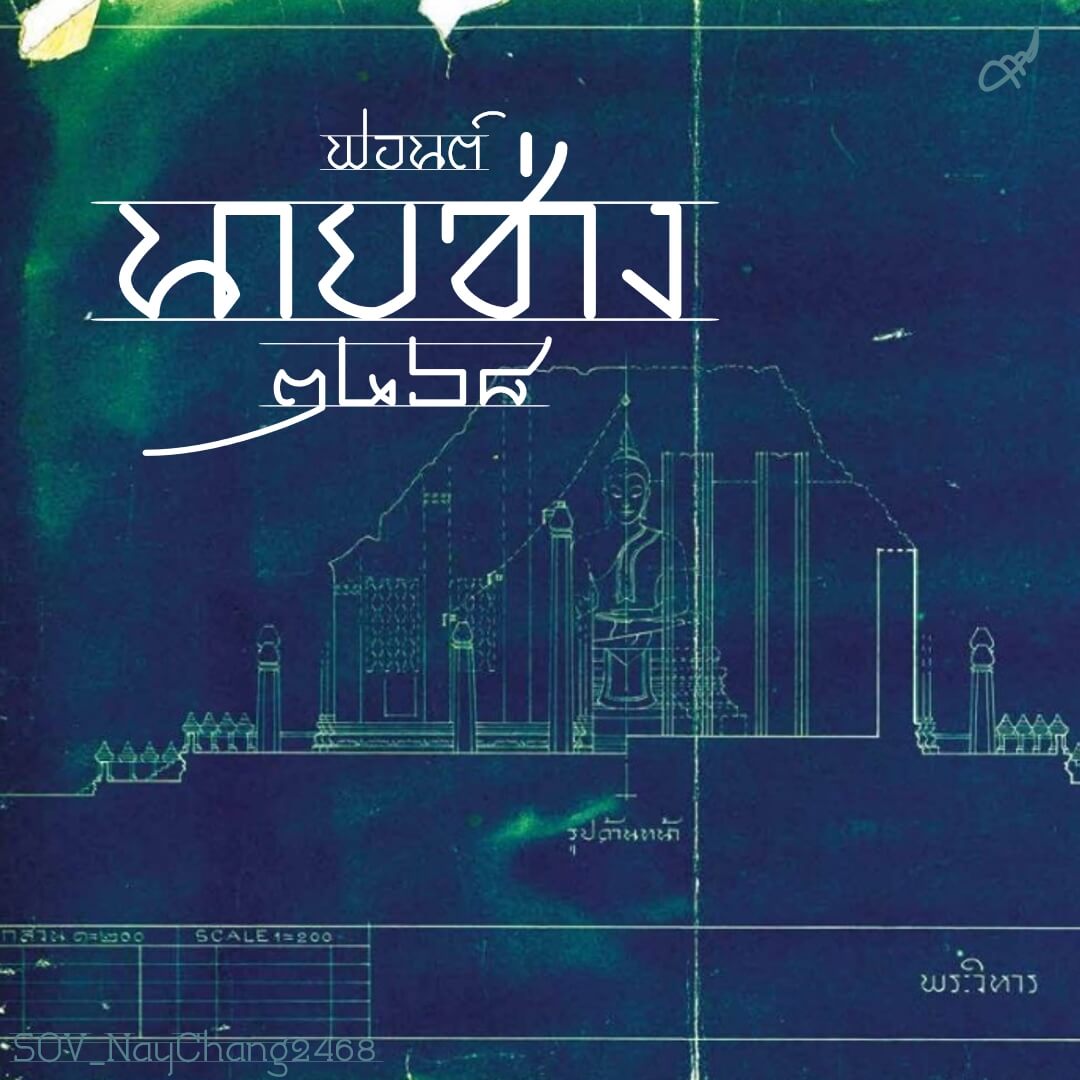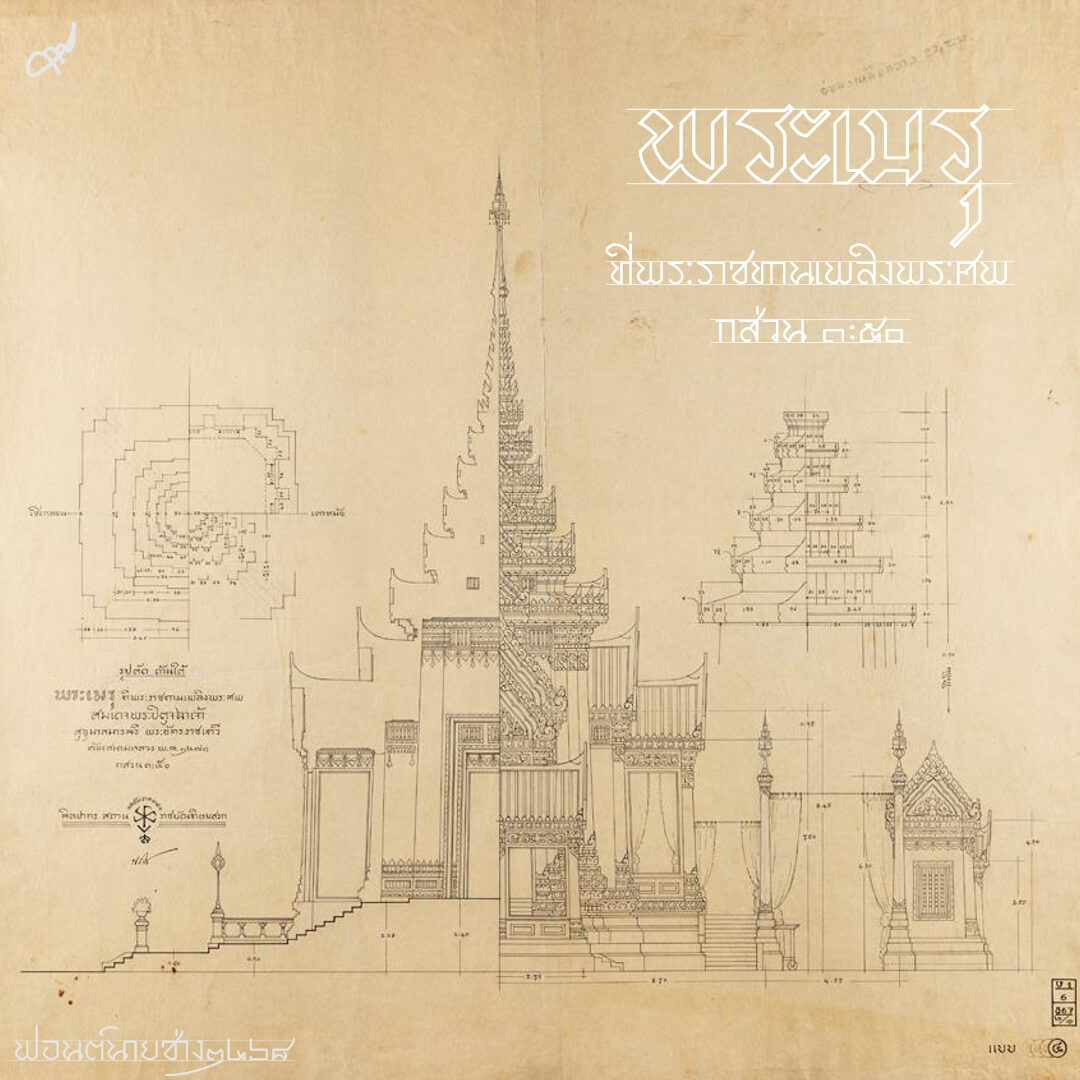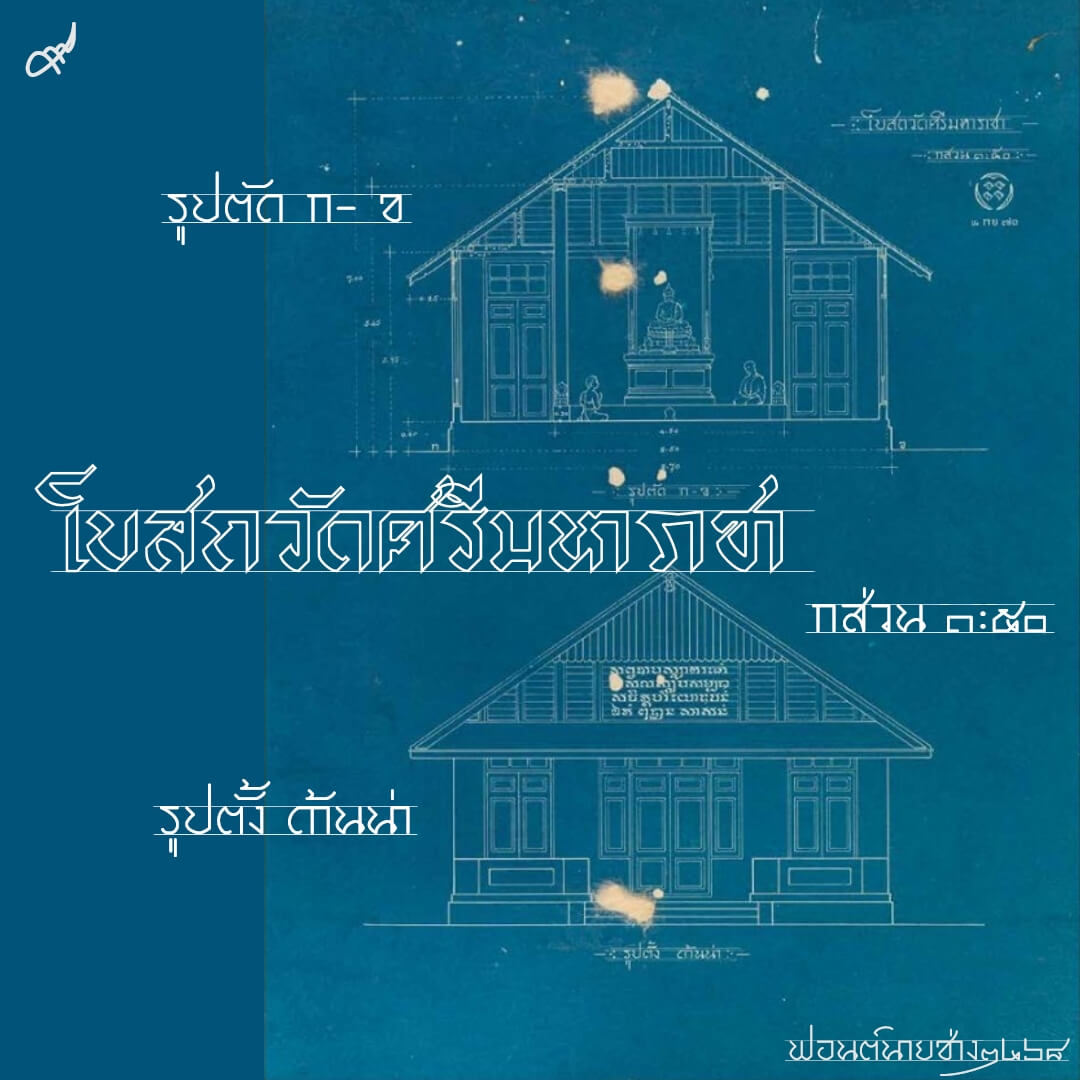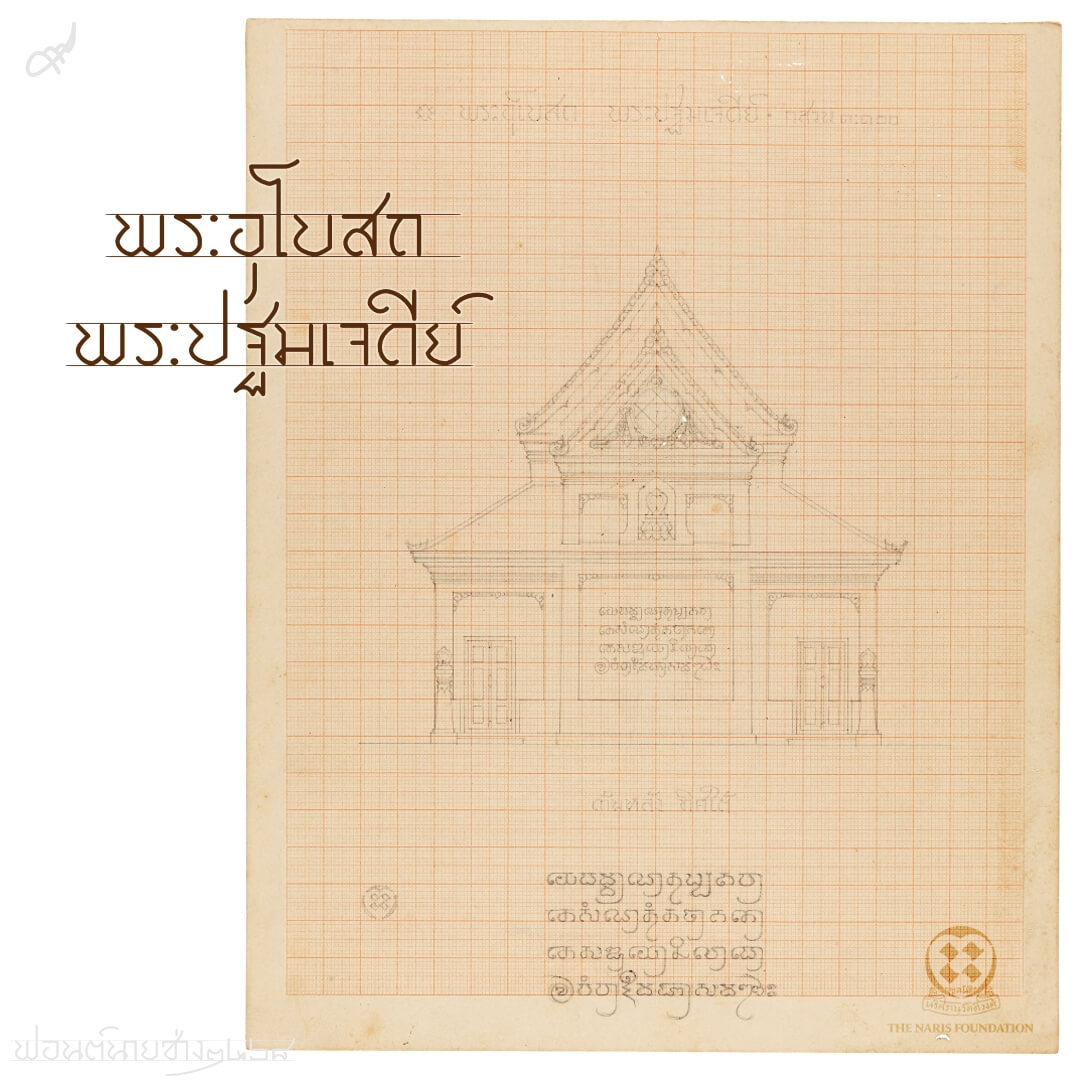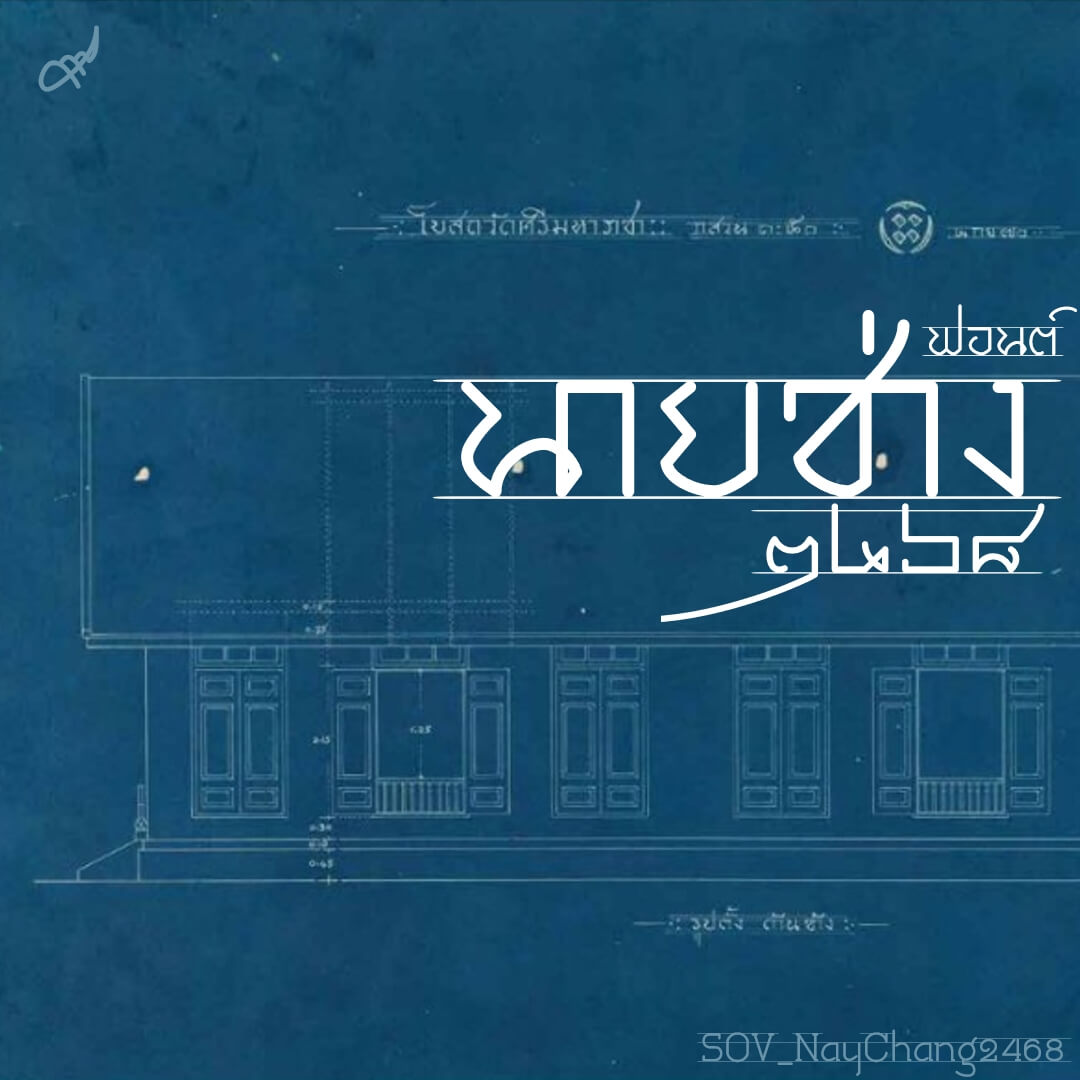
ฟอนต์นายช่าง2468 ต้นทางจากอักษรของสมเด็จครูที่พบในพิมพ์เขียวงานสถาปัตย์เมื่อประมาณร้อยปีที่แล้ว ร่างเส้นขึ้นมาใหม่ ชอบความมีเส้นบรรทัดเลยเติมเข้าไปด้วย ใช้เป็นข้อความ
หากอยากได้พาดหัวให้กด bold
เบื้องหลังการออกแบบ : ฟอนต์ นายช่าง2468
นายช่าง2468 (SOV_NayChang2468)